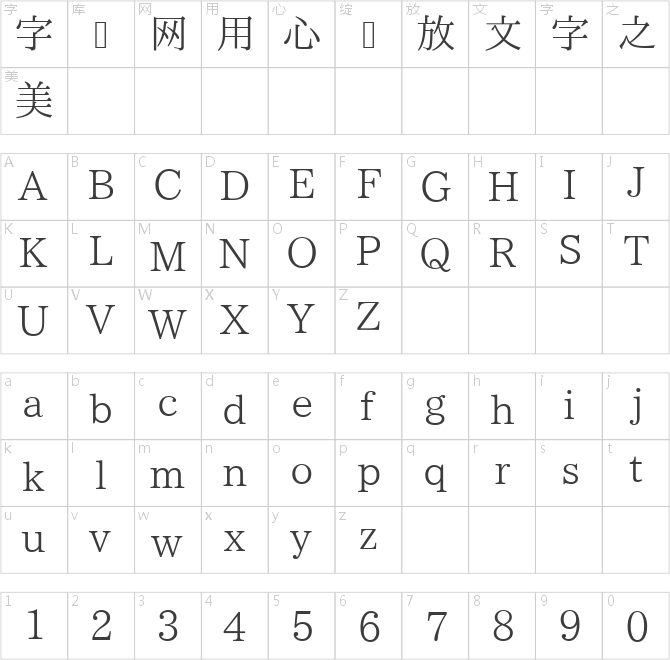
紫陽花明朝Z字體下載AjisaiMinchoZ
紫陽花明朝Z是一款充滿古典味道的免費商用宋體字形,紫陽花,又名八仙花、紫陽花、七變化、粉團花,原產(chǎn)于中國四川一帶及日本。相對于中國,紫陽花在日本更家喻戶曉,日本很多人都喜愛紫陽花,不少地方有紫陽花的種植園。詩人白樂天曾到某寺廟中,住持曾以該寺不知名的花朵詢問他,而他命名此花為”紫陽”。后來這名稱傳至日本,所以日本就稱此花為紫陽花。
這款字體以紫陽花命名,能讓人深深地感受到這款字體的優(yōu)雅之處,特別適合古典風(fēng)格的海報設(shè)計。在日本,一般會把宋體字形稱為明朝體。由于紫陽花明朝Z是由日本的設(shè)計師制作,所以字符是以JIS水準為標準,對簡體的支持比較差,但是對繁體支持很好。
紫陽花明朝Z字體AjisaiMinchoZ字庫是一款讓人賞心悅目、百看不厭的中文字體,適合各類廣告和產(chǎn)品包裝設(shè)計應(yīng)用,字體大小7.22MB,格式為ttf字體,上傳用戶是改一個名字呀,作者/版權(quán)方為未知